2023 年 36 种最佳企业字体(免费和付费)
已发表: 2023-08-05您是否曾经努力为您的公司项目寻找完美的字体? 您是否厌倦了那些无法达到您想要的效果的旧字体?
好吧,别再看了! 在这篇博文中,我们整理了 36 种最佳企业字体的列表,它们将使您的设计项目更上一层楼。
无论您是在创建徽标、网站还是印刷材料,这些字体都一定能提升您的设计并给人留下难忘的印象。
在当今的数字时代,字体对于品牌视觉识别的成功起着至关重要的作用。 他们可以传达公司的价值观、个性和专业精神。 选择正确的字体可以极大地改变受众对您品牌的看法。
在这份综合列表中,我们精心挑选了 36 种企业字体,这些字体已被证明可以增强品牌一致性、可读性和整体美感。 这些字体已被各个行业的顶级公司使用,并且经受住了时间的考验。
无论您是在寻找大胆而现代的字体来传达力量和创新,还是寻找经典而优雅的字体来传达更传统的感觉,您都会在本文中找到符合您愿景的字体。
准备好发现完美的字体,这将提升您的项目并给您的观众留下持久的印象。 排版世界触手可及!
最佳优质企业字体
希望用完美的字体提升您的设计项目? 我们列出的 36 种最佳优质企业字体就是您的最佳选择。 这些字体经过精心策划,可为任何项目增添专业性和精致感。
不要错过增强设计的机会 - 现在就查看本文中令人难以置信的字体选择。
派克
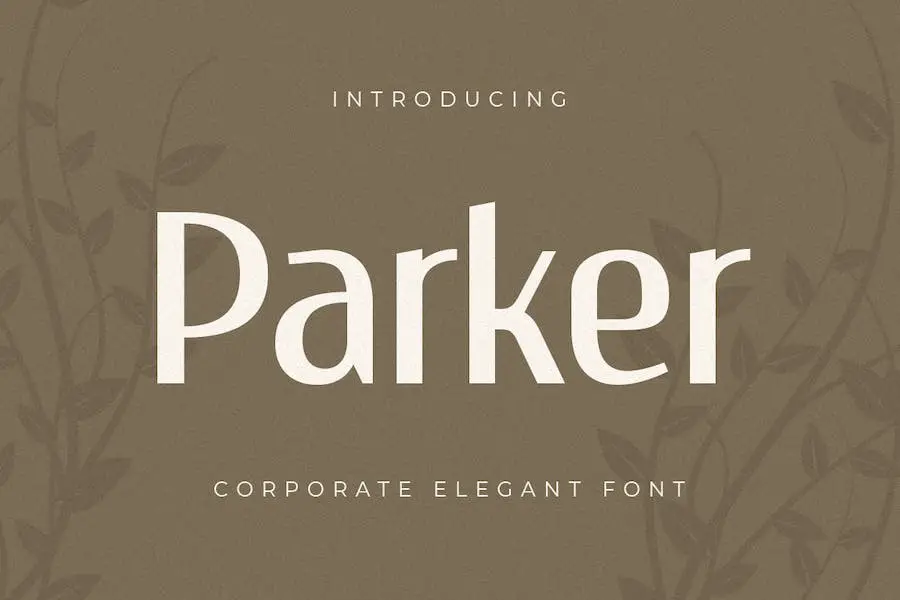
Parker 是一款令人惊叹的无衬线字体,完美融合了优雅和对比。 它专为品牌推广而设计,一定能为任何项目增添一丝精致和现代感。
凭借其广泛的连字和替代字符,该字体允许设计师和产品所有者释放他们的创造力并创造与他们的艺术愿景完美契合的无限变化。
通过使用 Parker,您可以确保您的设计脱颖而出,并给观众留下持久的印象。 其大胆而独特的外观引人注目,并营造出一种信任和可靠的感觉。
无论是徽标、标题还是标语,这种字体无疑都会发表声明并增强项目的整体视觉吸引力。
心态
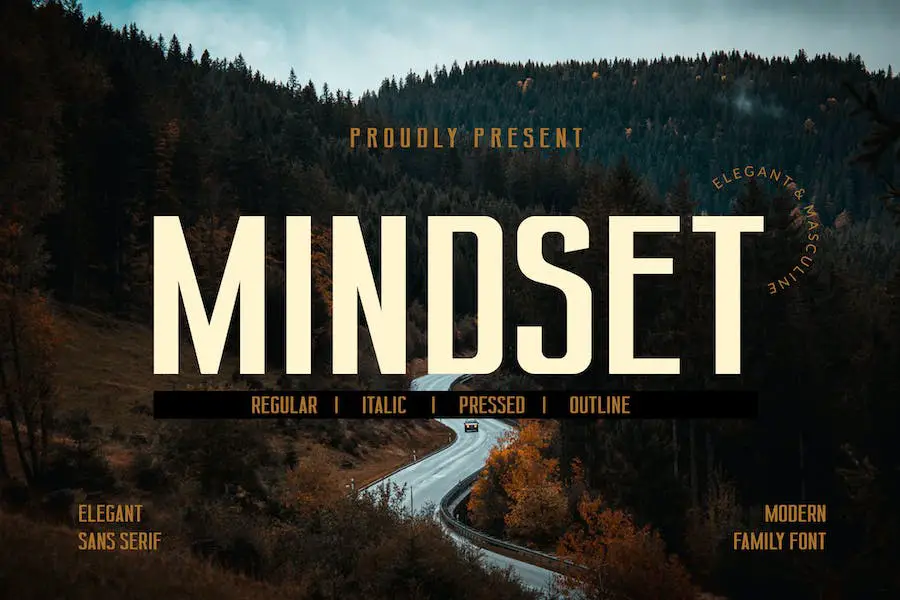
对于希望通过专业精神增强其项目的图形设计师来说,Mindset 是完美的字体。 使用这种字体,您可以轻松创建令人惊叹的徽标,可在网站、印刷品、杂志、海报等各种平台上使用。
专为徽标和品牌设计,每个角色都经过精心制作,以确保设计具有视觉吸引力和影响力。
当谈到企业无衬线字体时,Mindset 是最有力的竞争者。 其简洁的线条和大胆的结构散发出自信和专业精神,使其成为希望给人留下深刻印象的企业的理想选择。
无论您是为时尚的科技初创公司还是复杂的律师事务所创建徽标,这种字体都一定会提升您的设计并捕捉您品牌的精髓。
诺德黑德
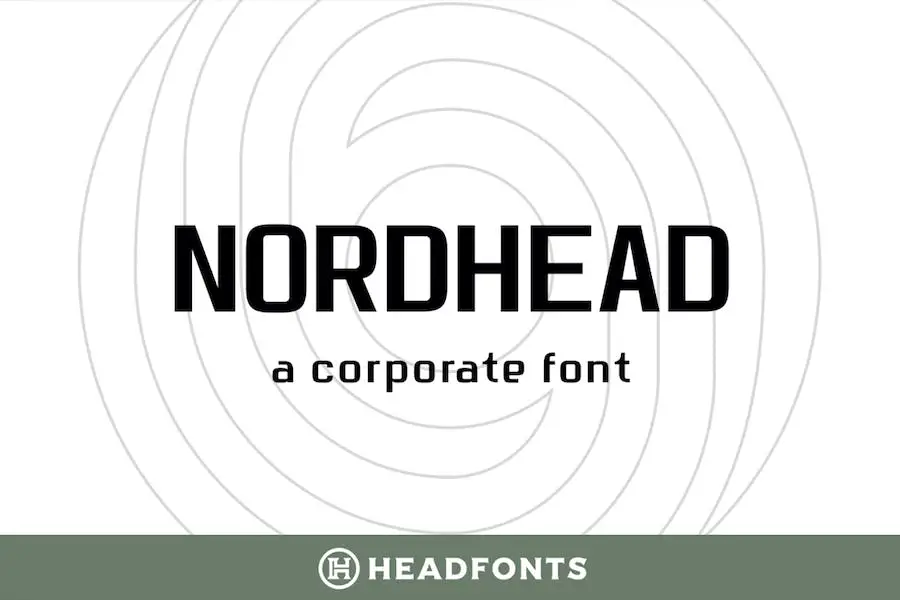
Nordhead 是一款时尚、现代的企业字体,将大写和小写字符与大胆、现代的美感和微妙的曲线相结合。
凭借其简洁且多功能的设计,该字体是为商业和企业品牌创建简约且简单的设计的完美选择。 Nordhead 非常适合标题和海报,也适合较小的文章和偶尔的文本。
该字体提供广泛的语言支持,包括 258 个字形、全套 AZ 字符、数字和标点符号。
如果您是一名平面设计师,希望通过时尚且专业的字体来增强您的项目,那么 Nordhead 绝对值得考虑。
美味的送货
Yummy Delivery 是一种非常适合为食品配送服务创建企业形象的字体。 它是一种明亮宜人的字体,带有装饰元素,为您的设计增添一抹魅力。
使用 Yummy Delivery,您不仅可以获得一种字体,还可以选择四种不同的字体:主字体、装饰字体、模糊字体和轮廓字体。
所有四种字体都带有大小写字母、数字、标点符号和多语言字符,使其适用于任何项目。
因此,无论您是设计菜单、徽标还是宣传材料,Yummy Delivery 都能满足您的需求。
商业签名
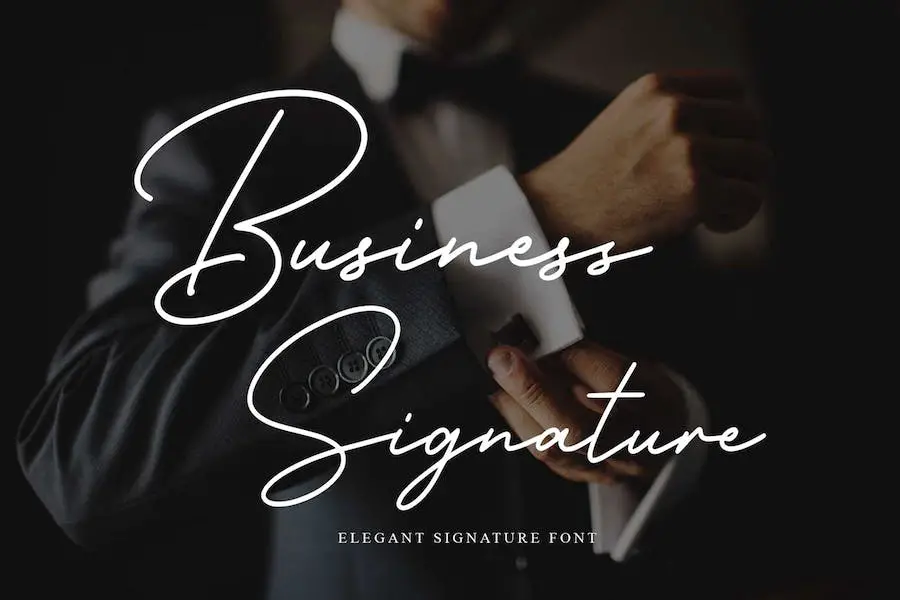
推出 Business Signature,这是一种优雅而现代的脚本字体,旨在为您的项目增添优雅和精致。
该字体从优雅和优雅的概念中汲取灵感,提供了美丽排版的和谐融合,使其成为各种设计工作的理想选择。
凭借其干净、精致的美感,Business Signature 是任何企业形象项目的完美选择。 其流畅的线条和时尚的曲线营造出优雅的感觉,将您的设计提升到新的高度。
无论您是为企业创建专业徽标还是制作引人注目的社交媒体帖子,这种字体都会吸引您的受众并留下持久的印象。
商业签名的突出特点之一是其多功能性。 这种字体无缝适应不同的设计环境,使其适用于各种项目。
赫洛维蒂卡
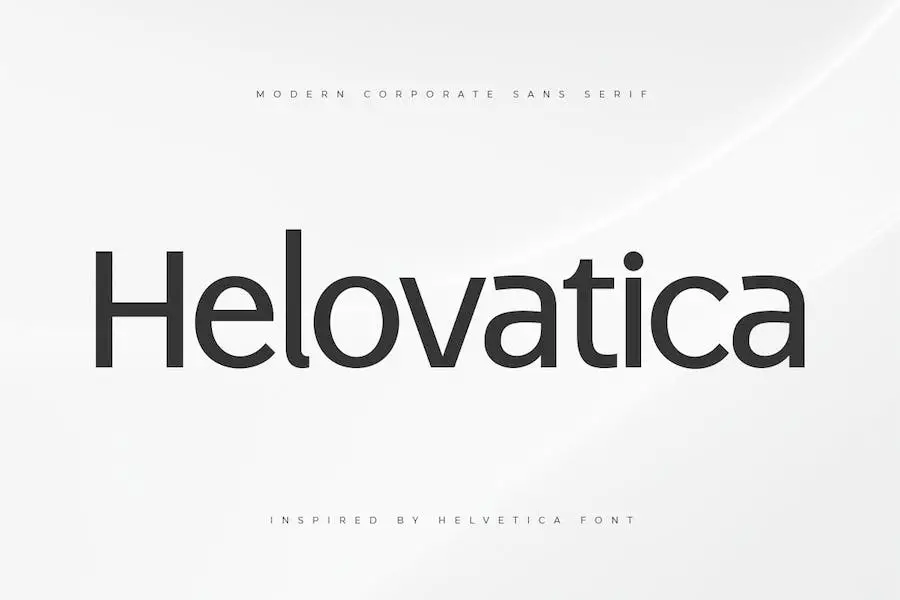
Helovatica 是一款出色的企业无衬线字体,散发着现代、优雅和独特的感觉。 对于任何希望通过一流的方式增强其项目的图形设计师来说,它是完美的选择。
该字体专为徽标设计项目而设计,非常适合创建需要现代风格的令人惊叹的徽标。
但它并不止于此 – Helovatica 用途广泛,可用于广泛的应用,包括品牌、杂志布局、社交媒体图形等。
凭借其时尚精致的外观,这种字体一定会提升任何需要现代和精致氛围的项目的设计。
罗纳德
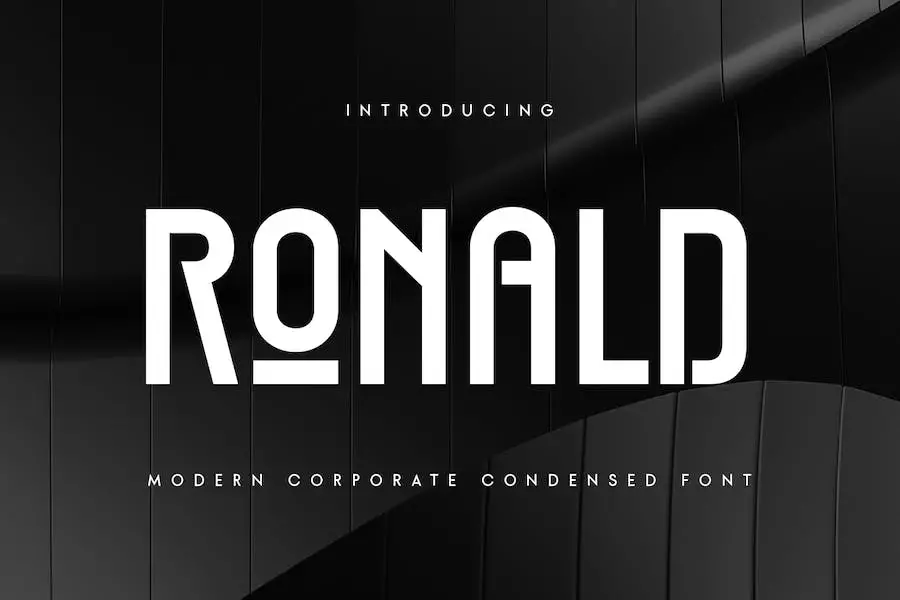
Ronald 是一种新型压缩无衬线字体,专为标题、标题和版式需求而设计。 它是添加您的个人风格并增强设计项目整体外观的完美选择。
该字体经过专门设计,可为您的标题提供独特而现代的感觉,让您以视觉上吸引人的方式展示您的主要想法。
与 Ronald 一起,您可以轻松创建引人注目的专业设计来吸引您的观众。 无论您是在制作网站、徽标还是任何其他设计项目,此字体都将帮助您产生强烈且令人难忘的影响。
Ronald 的简洁特性使其非常适合在有限的空间中容纳更多文本,而不会影响可读性或美观性。
其简洁的线条和锋利的边缘赋予其时尚和现代的外观,使其成为企业品牌、广告或任何需要大胆和专业风格的设计的绝佳选择。
垫片
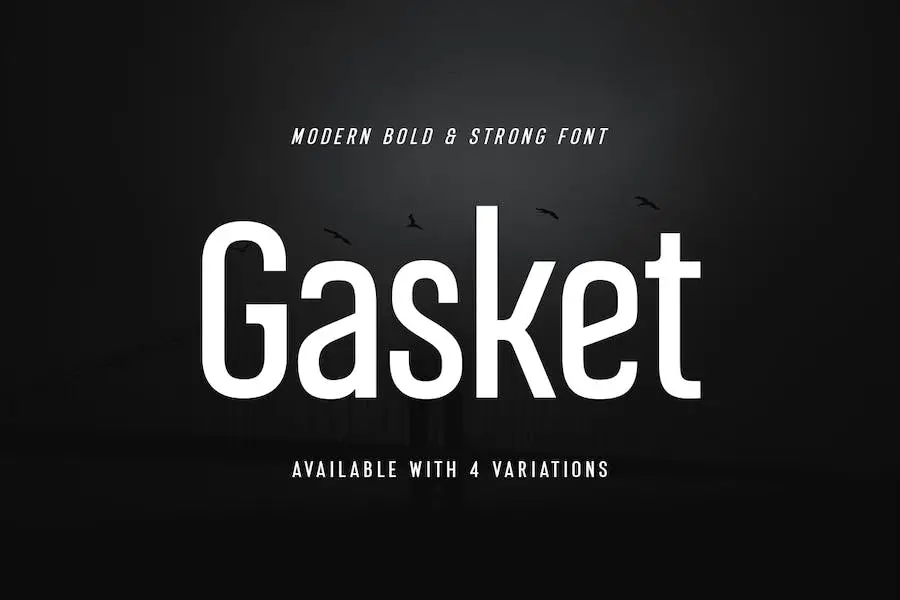
Gasket 是一种新的 Sans Serif 字体,专为商业和企业项目创建。 通过额外的轮廓和斜体版本,它为您的设计增添了独特的触感。 其干净而现代的风格使其非常适合提案并以出色的方式展示您的主要想法。
Gasket 旨在提升项目的视觉吸引力并提供专业的触感。 无论您是在制作商业演示、企业品牌还是提案,这款字体都能满足您的需求。
其大胆而简洁的线条使其易于阅读,而额外的轮廓和斜体版本则为您提供了多功能性和选择。
这种字体非常适合传达您的价值主张并给人留下深刻的印象。 Gasket 的干净感觉将增强您项目的整体美感,并帮助您在竞争中脱颖而出。
其现代时尚的设计散发着专业精神和自信,使其成为任何企业环境的绝佳选择。
企业标志
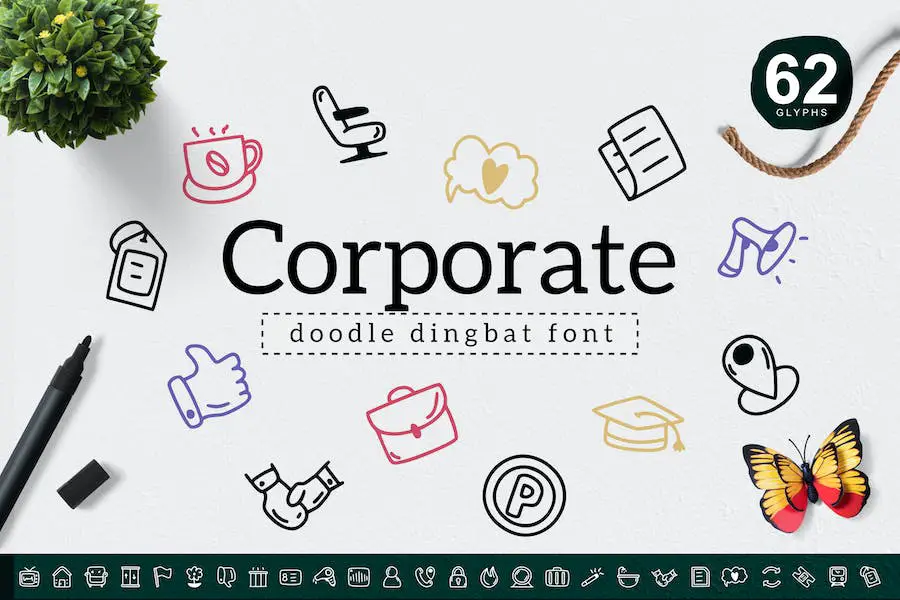
Corporate Dingbat 是一种多功能且用户友好的字体,非常适合希望增强项目设计的图形设计师。
这款简单的企业涂鸦 dingbat 字体包含 62 个符号,适用于徽标、装饰品等多种应用。
该字体为任何设计增添了一丝专业气息,赋予其精致而精致的外观。 其简洁的线条和简约的风格使其能够轻松融入各种项目,确保具有凝聚力和专业的外观。
无论您是从事企业品牌项目、为客户制作徽标,还是寻求增强设计的视觉趣味,Corporate Dingbat 都提供了多种符号可供选择。
它的多功能性提供了无限的创意可能性,使设计师能够为他们的作品添加独特的风格和元素。
这种字体的设计考虑到了图形设计师的需求,易于使用和导航。 其用户友好的界面确保无缝体验
攻击
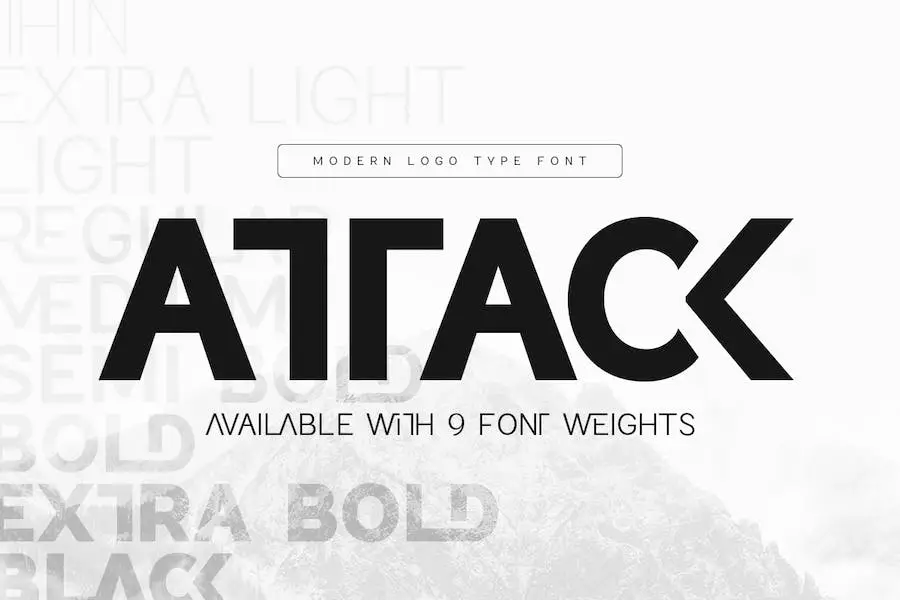
Attack 是一款时尚而现代的企业徽标无衬线字体,将提升任何项目的设计。 其简约和标志性的风格使其成为品牌项目、标志设计和海报设计的完美选择。
凭借其独特的形状和易于组合的连字,您可以在短短几秒钟内创造出无尽的变化来满足您的创意愿景。
这种字体不仅美观,而且具有很高的易读性。 无论您是设计社交媒体帖子、广告、产品包装还是标签,Attack 都将确保您的信息清晰且易于理解。
它也是摄影水印、邀请函和文具的绝佳选择,为您的项目增添一丝精致感。
Attack 的多功能性使其成为图形设计师的宝贵资产。 其简洁的线条和大胆的外观使其适合广泛的应用。
无论您想要专业、精致的外观还是更现代、前卫的感觉,这款字体都能满足您的需求。
帕尼斯科贝
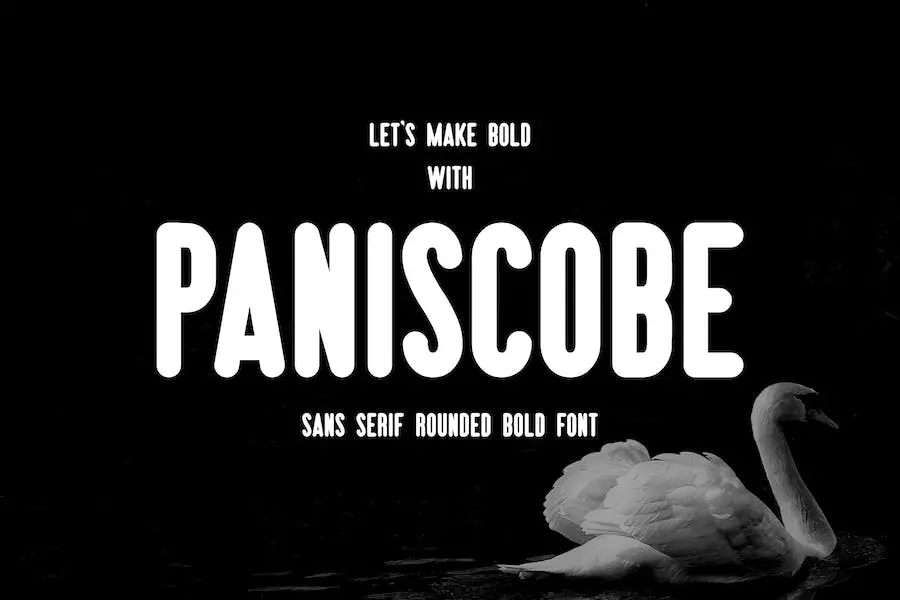
Paniscobe 是一种大胆的企业字体,散发着专业和自信的感觉。 其厚重的外观引人注目,并为其所使用的任何项目留下持久的印象。
无论您是设计时尚的公司徽标还是创建引人注目的营销材料,Paniscobe 都是将您的设计提升到新水平的字体。
Paniscobe 凭借简洁的线条和强大的存在感,确保您的信息响亮而清晰地传达。 其粗笔画使每个字符脱颖而出,即使从远处也能轻松阅读。
无论是在网站、海报还是名片上,Paniscobe 都能确保您的文字不会被忽视。
这种企业字体非常适合传达力量和可靠性感。 它非常适合金融、技术和咨询等信任和信誉至关重要的行业。
FT Getcode Pro
FT Getcode Pro 是一个现代的板衬线字体系列,可以极大地增强您的公司或企业项目的设计。
凭借其多功能性,这种字体可以应用于广泛的创意,使它们真正脱颖而出。 将 FT Getcode Pro 融入您的设计中将为您的设计带来专业而精致的外观,提升您的品牌形象并吸引注意力。
无论是徽标、网站标题还是营销材料,这种字体一定会产生持久的影响。 使用 FT Getcode Pro 扩展您的创意可能性,并见证它可以为您的商业字体带来的改变。
克里克显示器
Krick Display 是新一代字体,专为增强您的品牌吸引力而设计。 这种字体有四种粗细可供选择,不留任何细节。 从企业项目到徽标、标题和数字广告,Krick 的多才多艺足以处理这一切。
无论您是要创建品牌材料、标题、海报还是显示屏,这种字体都能满足您的需求。 其细致的设计确保每个元素完美结合,使 Krick 成为希望给人留下持久印象的设计师的终极选择。
加马拉萨
Gamarasa 是一种大胆的机器人风格显示字体,非常适合为您的设计项目添加独特的风格。 无论您的徽标、标题还是任何创意活动需要字体,Gamarasa 都能满足您的需求。
凭借其时尚和现代的设计,该字体适用于各种应用,例如企业形象、品牌形象、海报、音乐、电影、各种游戏、杂志、书籍、漫画、卡通、YouTube、Instagram、网站等。
Gamarasa 的突出特点之一是其大胆且引人注目的外观。 简洁的线条和强烈的几何形状赋予这种字体机器人和未来主义的氛围,使其成为需要现代和前卫外观的项目的完美选择。
它会立即吸引观众的注意力,并使您的设计在人群中脱颖而出。
此外,Gamarasa 的用途非常广泛,可以轻松融入各种设计主题和风格。
无论您正在从事时尚简约的企业项目,还是有趣且充满活力的海报设计,此字体都可以适应您的需求并增强您工作的整体视觉效果。
普罗克斯
Prox 是一款创新的企业字体,可为您的设计项目带来现代优势。 这种窄宽度无衬线字体非常适合设置大尺寸和小尺寸的文本。
略显方形的比例赋予其独特而原创的外观,而规则的字母形式则给人一种熟悉的感觉。 无论您是在制作宣传册、徽标还是网站,Prox 都会为您的设计增添一丝精致和专业精神。
通过选择符合公司价值观和目标受众的字体,企业可以为客户创造视觉上令人愉悦且难忘的体验。
选择企业字体时应考虑几个因素。 首先,它应该与公司的品牌形象相一致,体现公司的个性。 其次,易读性至关重要,尤其是在不同的媒介和尺寸之间。
此外,字体应该足够通用,可以用于各种营销材料。 最后,考虑目标受众和行业趋势可以帮助选择与合适的人产生共鸣的字体。
结论
总之,我们探索了 36 种可以提升项目设计的最佳企业字体。 从经典优雅到现代时尚,这些字体提供了广泛的选择来满足您的企业设计需求。
请记住进行试验并找到最适合您的品牌个性和信息的字体。